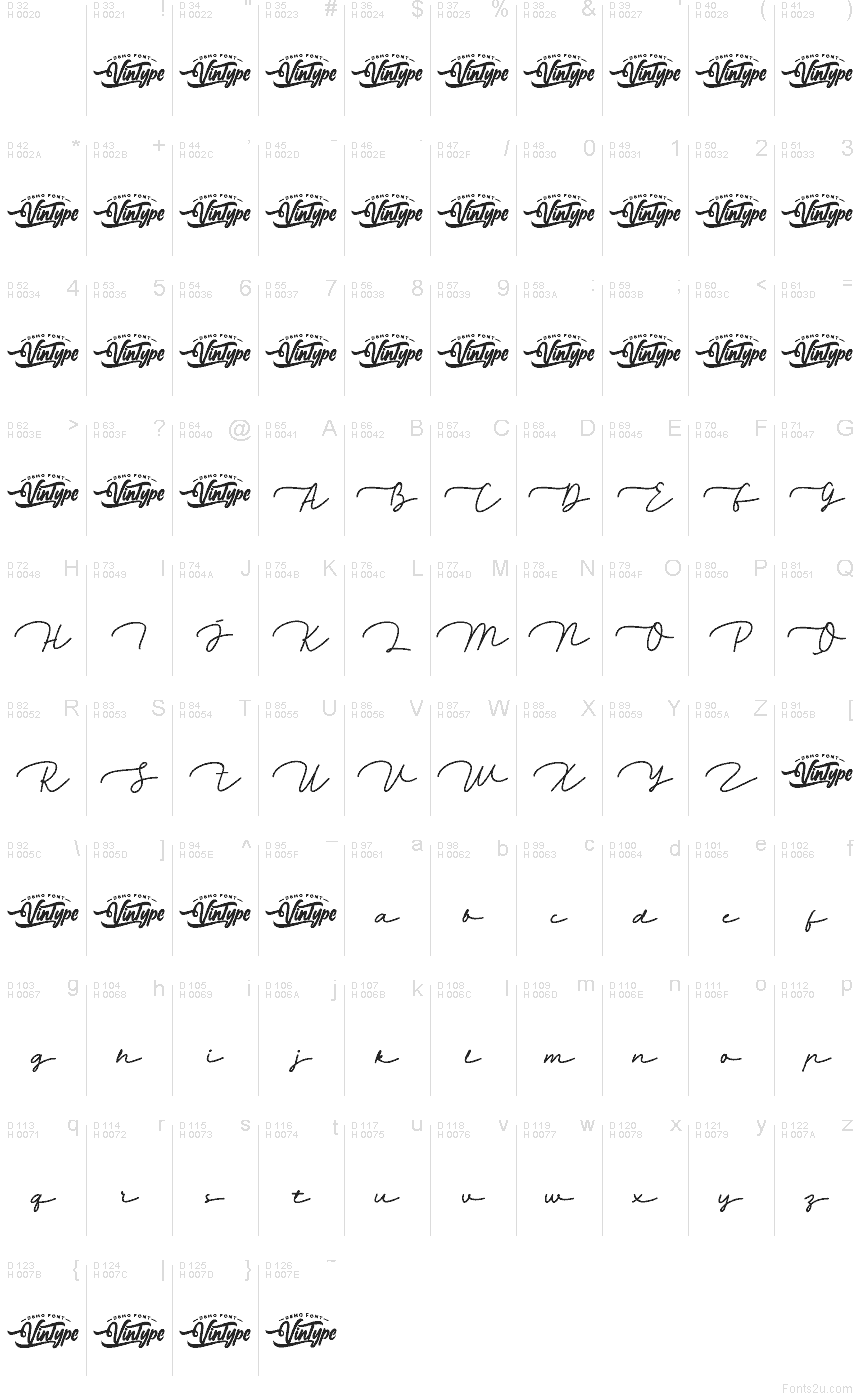
Stelena Demo Script
Stelena Script od VinType Studio je bezplatné ručne písané písmo, ktoré definujú dlhé, rozmáchle ťahy a uvoľnený kurzívny rytmus. Veľká úvodná slučka a rovnomerný, plynulý pohyb po zvyšku písmen mu dodávajú pocit rýchleho podpisu, nakresleného s absolútnou istotou.
Táto ľahkosť výborne funguje pri butikových logách, obaloch, svadobných tlačovinách, citátoch na sociálnych sieťach a v kozmetickom brandingu, kde osobný charakter zaváži viac než formálna štruktúra. Písmo sa hodí aj na etikety produktov alebo nadpisy blogov, najmä ak hľadáte font, ktorý si vďaka širokým krivkám zachováva pôvab a nie je preplnený detailmi.